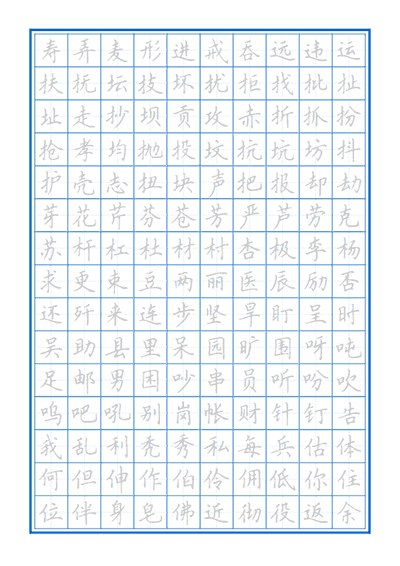
简介:《【字帖大全 电子字帖 练字】》是一个包含多种电子字帖的合集,旨在帮助用户提升书写水平。字帖可能涵盖楷书、行书、隶书等多种字体,以及不同风格的书法作品。用户可以根据自己的喜好和需求选择相应的字帖进行练习,通过在电子设备上临摹或打印出来练习,提高笔画书写规范度、字体结构把握能力,适合书法初学者、想要提升书写美观度的学生和书法爱好者使用